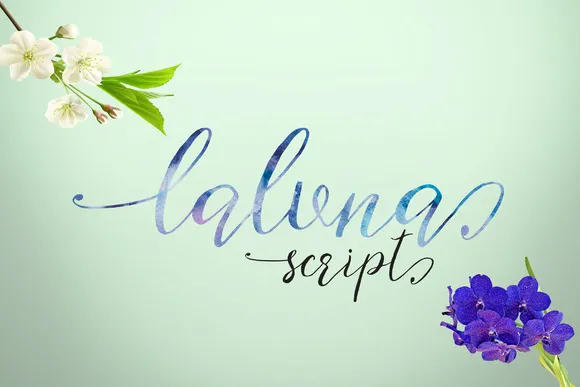
Laluna Script Font
Laluna Script é uma nova variedade de fontes script escritas à mão, oferecendo ao designer uma grande liberdade para criar cada palavra com um estilo único e distintivo. Esta fonte traz consigo uma aparência suave e elegante, caracterizada por linhas longas e finas que dão a impressão de luxo e originalidade. Perfeita para quem busca uma fonte que não só é prática no dia-a-dia do design gráfico, mas também oferece um toque refinado em projetos pessoais ou profissionais. Com sua versatilidade e personalização, Laluna Script se destaca entre outras fontes script, proporcionando aos designers a chance de criar textos que transmitem uma sensação única e sofisticada.